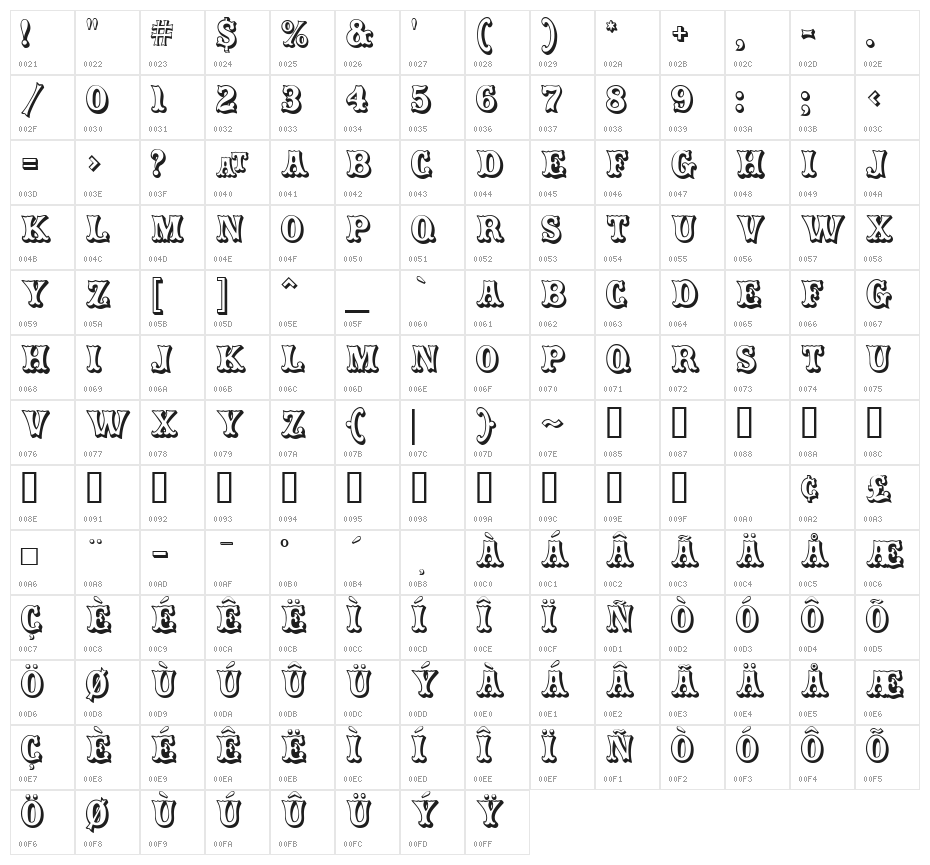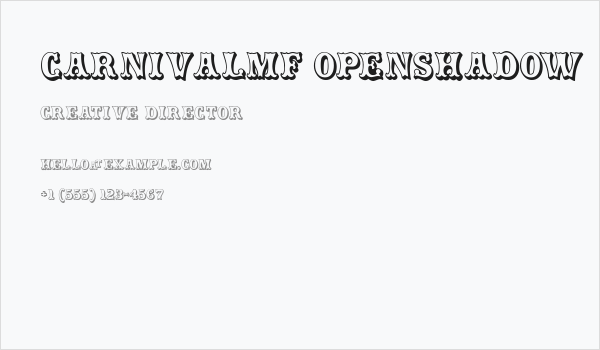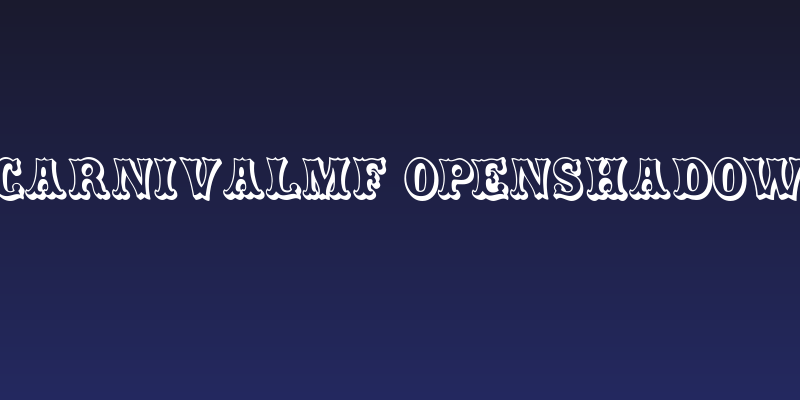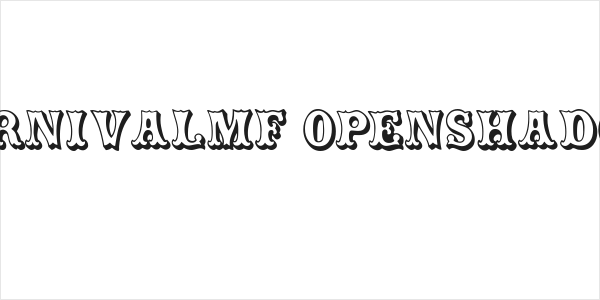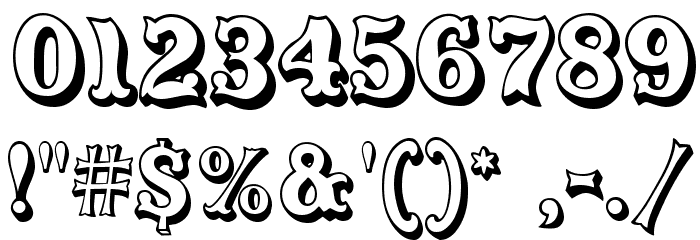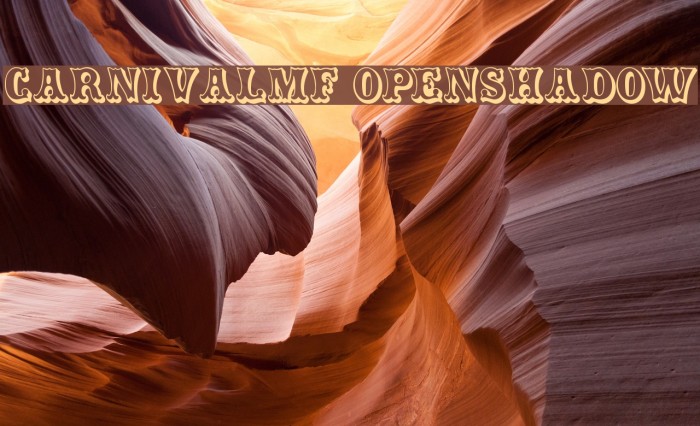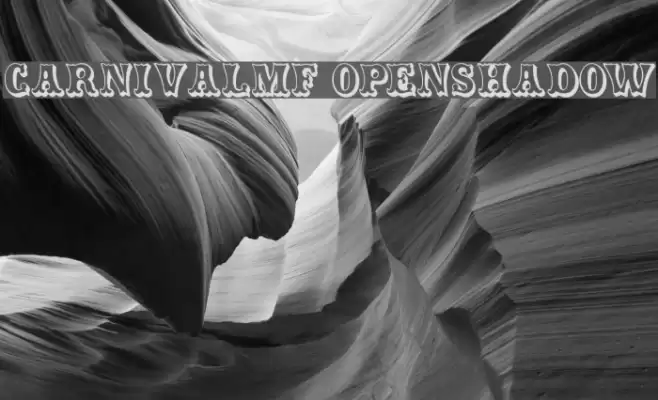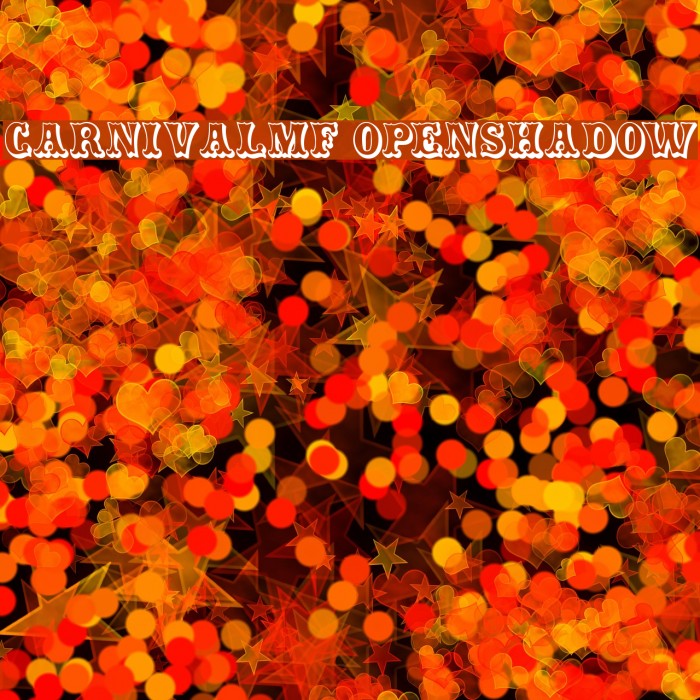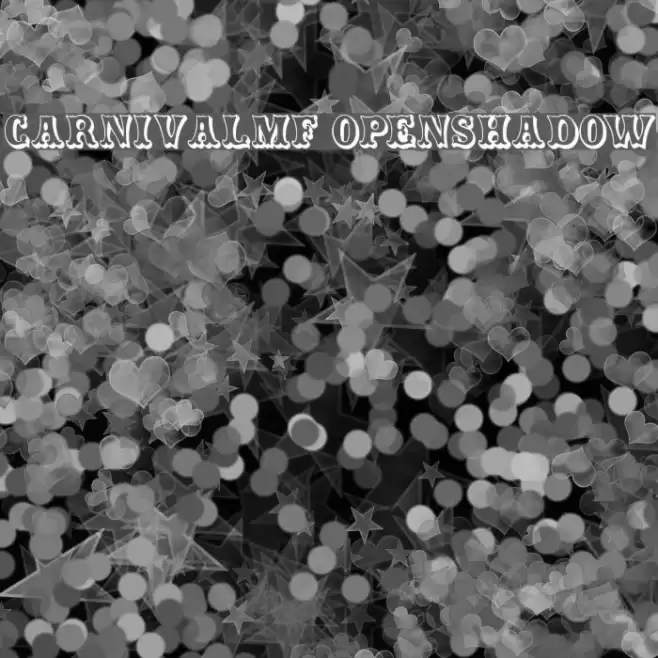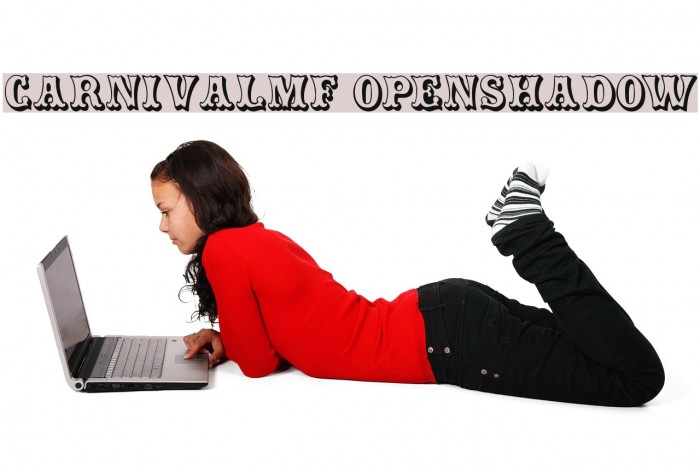
CarnivalMF OpenShadow Font
| Категория | Retro |
| Общий стиль | Vintage |
| Рекомендуемые проекты | Ideal for posters, event invitations, signage, and any design needing a festive, retro touch. |